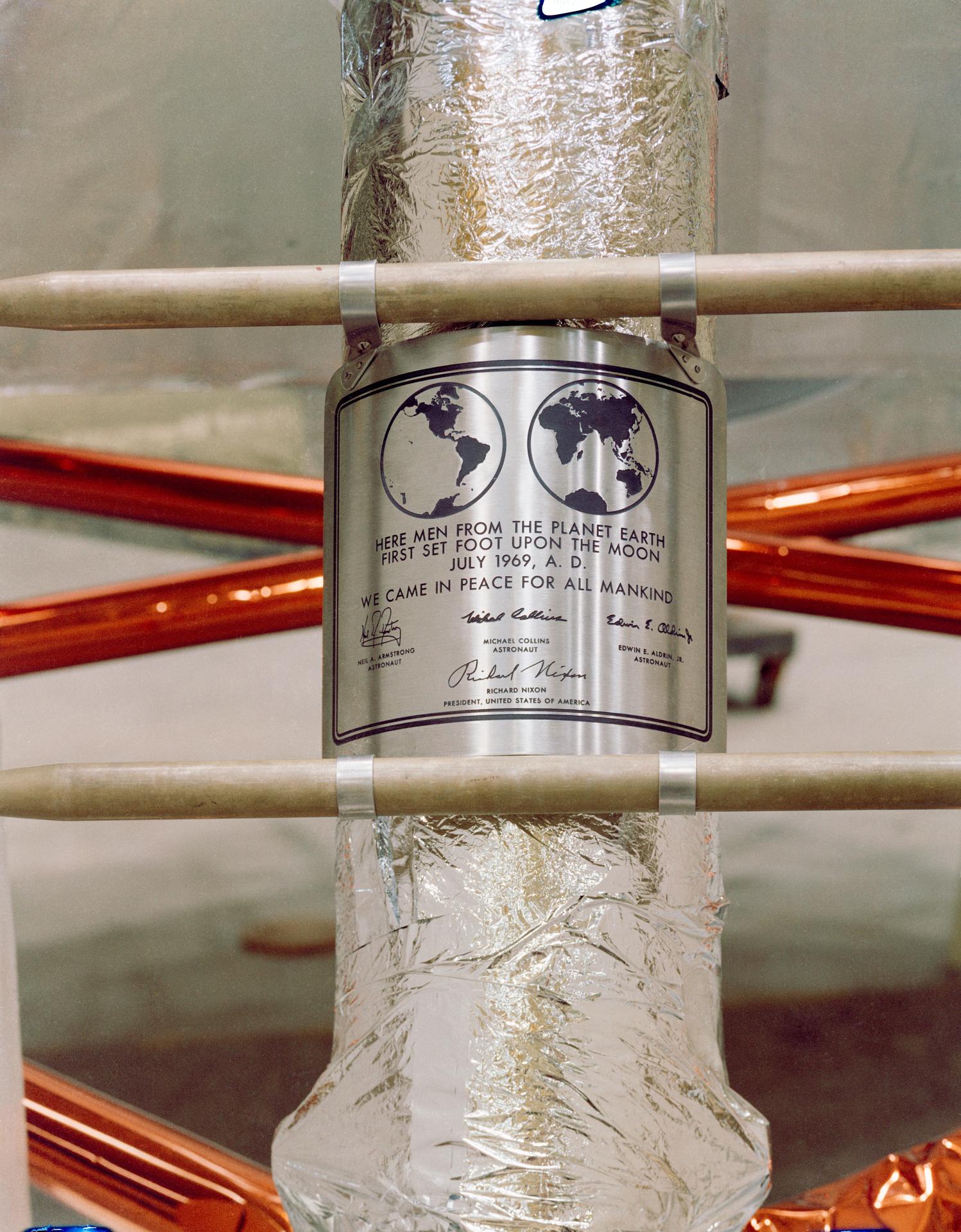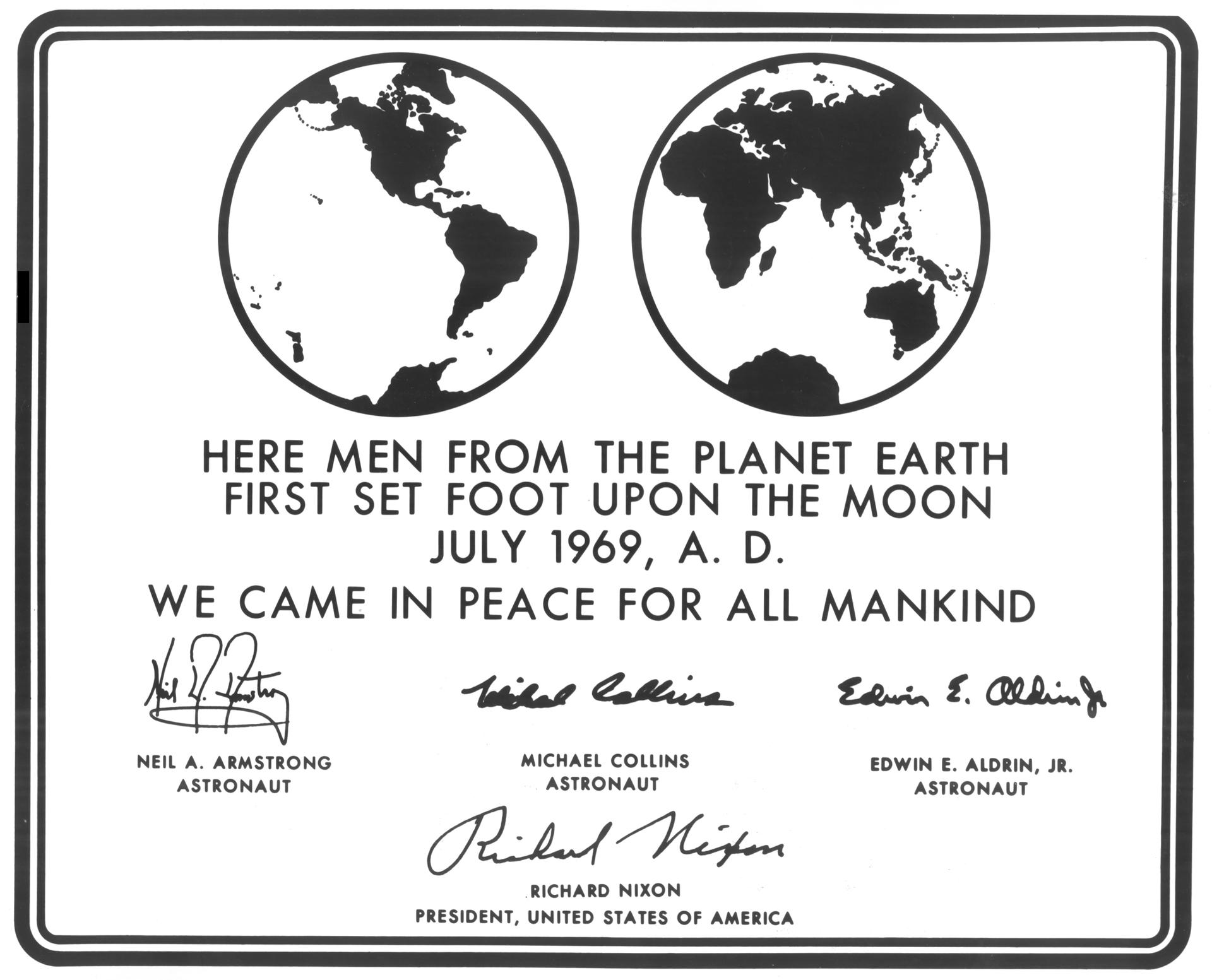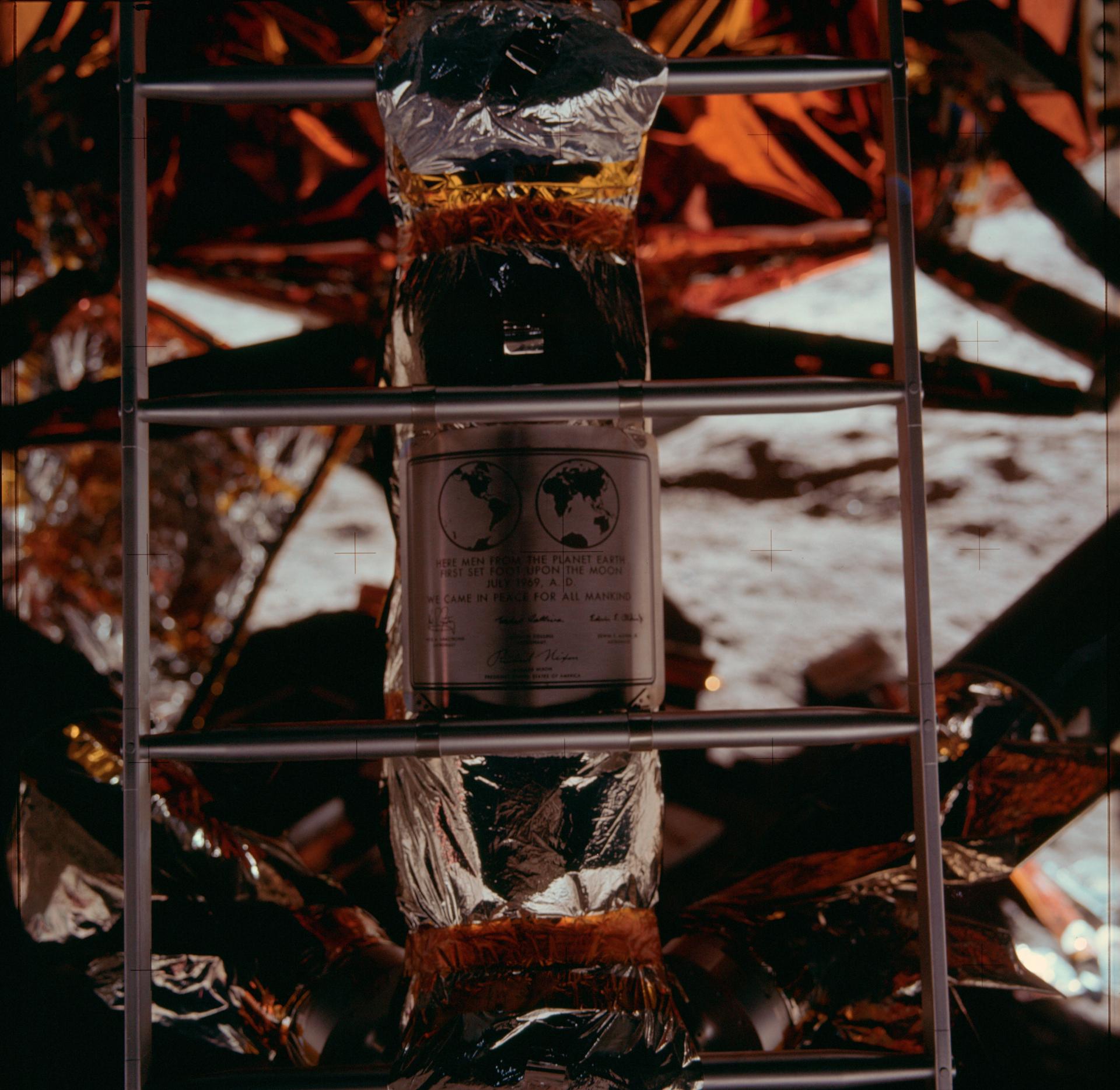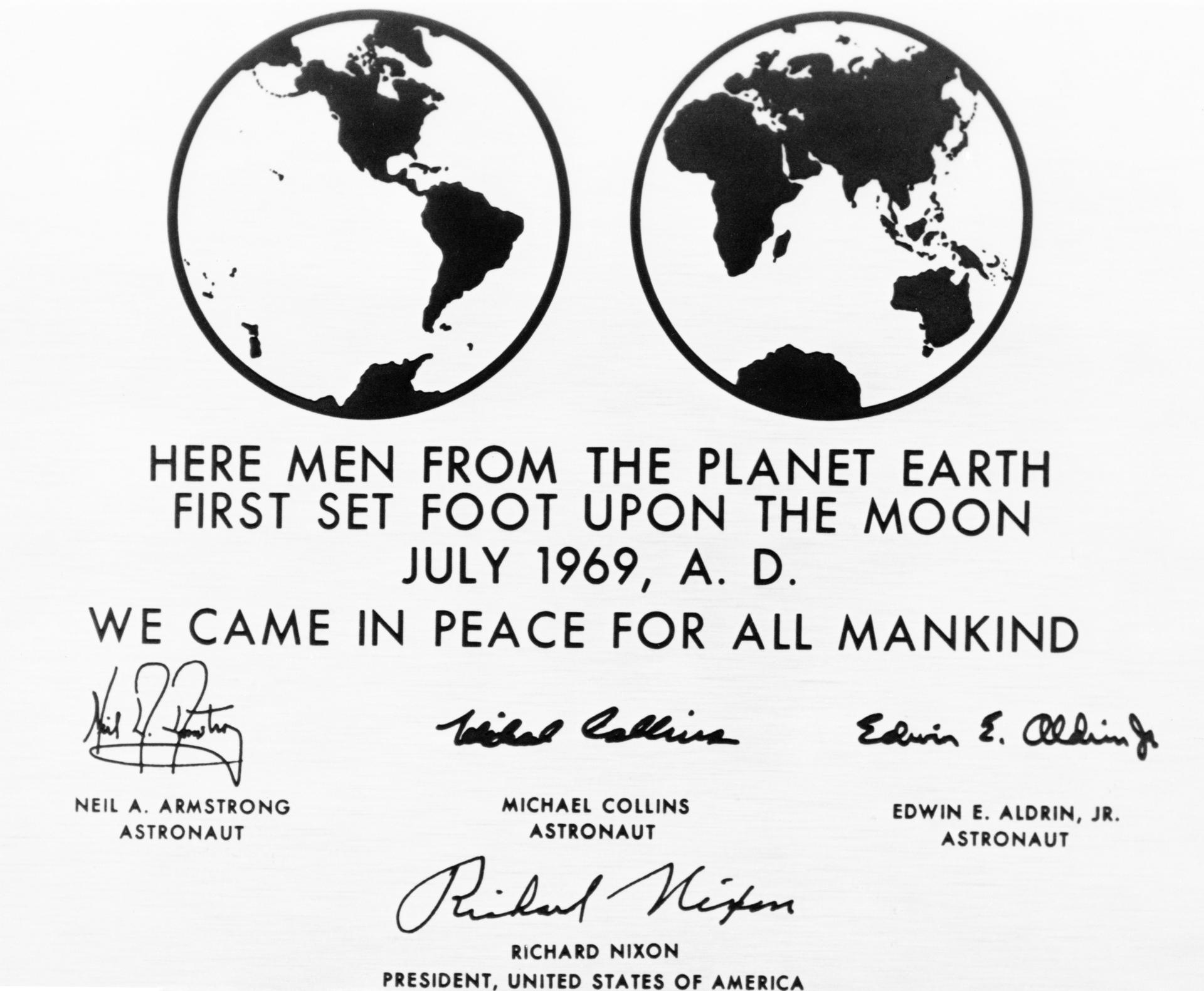
บนแผ่นโลหะสเตนเลสขนาดราวฝ่ามือ มีข้อความสั้นๆ สลักไว้ว่ามนุษย์จากดาวเคราะห์โลกได้มาเหยียบดวงจันทร์เป็นครั้งแรก เดือนกรกฎาคม ปี 1969 แผ่นนั้นยังอยู่ที่นั่น ติดกับขาของยานลงจอด ในที่ที่ไม่มีลมและไม่มีฝน และตัวอักษรบนแผ่นนั้นคือ Futura
แผ่นป้าย Apollo 11 บนดวงจันทร์ ตัวอักษรเป็นฟอนต์ Futura
Futura ไม่ได้เกิดมาเพื่อไปอวกาศ มันถูกออกแบบโดย Paul Renner นักออกแบบชาวเยอรมัน เสร็จในปี 1927 ในช่วงที่แนวคิดแบบ Bauhaus กำลังเปลี่ยนวิธีมองงานออกแบบทั้งหมด Renner สร้างตัวอักษรจากรูปทรงเรขาคณิตพื้นฐาน วงกลม สามเหลี่ยม สี่เหลี่ยม ตัว o เกือบเป็นวงกลมสมบูรณ์ ขาของตัวอักษรตรงและบาง ไม่มีลวดลายส่วนเกิน
ภาพระยะใกล้แผ่นป้าย Apollo 11 เห็นตัวอักษร Futura ชัดเจน
ชื่อ Futura มาจากคำที่แปลว่าอนาคต และมันก็ทำตัวสมชื่อ ในยุคที่ฟอนต์ส่วนใหญ่ยังอ้างอิงลายมือหรืองานแกะตัวพิมพ์แบบเก่า Futura เลือกตัดอดีตทิ้ง แล้วบอกว่าตัวอักษรไม่จำเป็นต้องเลียนแบบมือคน มันเป็นวัตถุที่ออกแบบได้ด้วยเหตุผลและรูปทรง ความคิดแบบนี้ทำให้มันดูเย็น สะอาด และไม่ผูกกับยุคสมัยใดยุคหนึ่งจนเกินไป
ความเป็นกลางตรงนั้นเองที่ทำให้มันถูกหยิบไปใช้ในที่ต่างๆ มากมาย ตั้งแต่โฆษณา บรรจุภัณฑ์ ปกหนังสือ ไปจนถึงโลโก้แบรนด์ระดับโลก มันไม่ตะโกน ไม่เรียกร้องความสนใจ แต่ทำงานเงียบๆ อยู่เบื้องหลังข้อความ คล้ายกับที่เราเคยเล่าถึง ฟอนต์ Johnston ของรถไฟใต้ดินลอนดอน ที่ดีจนคนแทบไม่ทันสังเกตว่ามันอยู่ตรงนั้นมานานแค่ไหน
แบบจำลองแผ่นป้าย Apollo 11 ก่อนภารกิจ ใช้ตัวอักษร Futura
เมื่อ NASA ต้องเลือกตัวอักษรไปสลักบนแผ่นที่จะอยู่บนดวงจันทร์ตลอดกาล Futura จึงเป็นคำตอบที่เข้าใจได้ มันอ่านง่าย ดูเป็นเหตุเป็นผล และไม่มีกลิ่นของชาติใดชาติหนึ่งหรือยุคใดยุคหนึ่งติดอยู่ ข้อความบอกว่ามาอย่างสันติเพื่อมวลมนุษยชาติ และตัวอักษรที่ใช้ก็พยายามไม่เป็นของใครเป็นพิเศษ เหมือนถูกออกแบบมาให้เป็นเสียงกลางๆ ของคนทั้งโลก
นักบินอวกาศ Buzz Aldrin ก้าวลงสู่พื้นผิวดวงจันทร์ในภารกิจ Apollo 11
มีรายละเอียดที่ชวนคิดอยู่ในเรื่องของ Renner เอง เขาต่อต้านแนวคิดของพรรคนาซีอย่างเปิดเผย และถูกบีบให้ออกจากตำแหน่งในเยอรมนีช่วงทศวรรษ 1930 ตัวอักษรที่เขาวางใจว่าควรเป็นเหตุเป็นผลและเป็นสากล สวนทางกับบรรยากาศการเมืองที่เขาอยู่ หลายสิบปีต่อมา ตัวอักษรชุดนี้กลับไปไกลกว่าที่ใครคาด ไปอยู่ในที่ที่การเมืองบนโลกตามไปไม่ถึง
แผ่นป้ายติดที่ขาของยานลงจอด Apollo 11 ตัวอักษร Futura
บนพื้นผิวดวงจันทร์ไม่มีการกัดกร่อนแบบที่เกิดบนโลก ไม่มีออกซิเจน ไม่มีน้ำ ไม่มีลมพัด แผ่นป้ายและตัวอักษร Futura บนนั้นจึงน่าจะคงรูปอยู่ได้นานกว่าสิ่งก่อสร้างเกือบทุกอย่างที่มนุษย์เคยทำบนโลก เป็นไปได้ว่ามันจะอยู่ที่นั่นนานกว่าตัวภาษาที่เราใช้เขียนมันด้วยซ้ำ
รอยรองเท้าบนพื้นผิวดวงจันทร์จากภารกิจ Apollo 11
เราคุ้นกับ Futura มากจนมองข้ามมันไปบนปกหนังสือ บนป้าย บนกล่องสินค้าในซูเปอร์มาร์เก็ต ตัวอักษรที่ดูธรรมดาที่สุดชุดหนึ่ง กลับเป็นตัวอักษรชุดแรกที่ออกไปอยู่นอกโลก คราวหน้าที่เห็นวงกลมเรียบๆ ของตัว o แบบ Futura ที่ไหนสักแห่ง อาจลองนึกว่ารูปทรงเดียวกันนี้ กำลังนิ่งอยู่บนดวงจันทร์มาเกือบหกสิบปีแล้ว